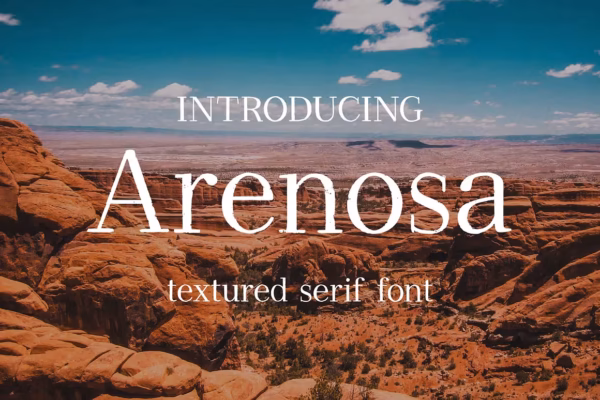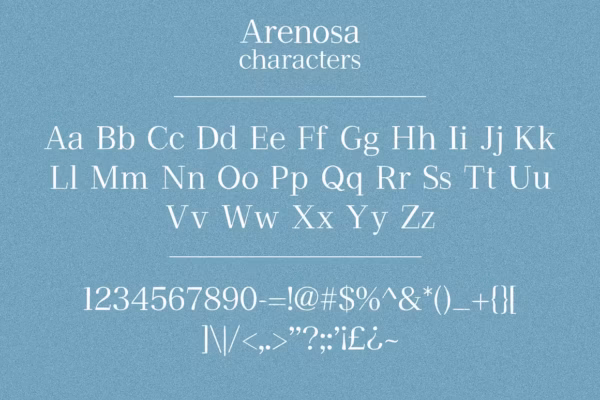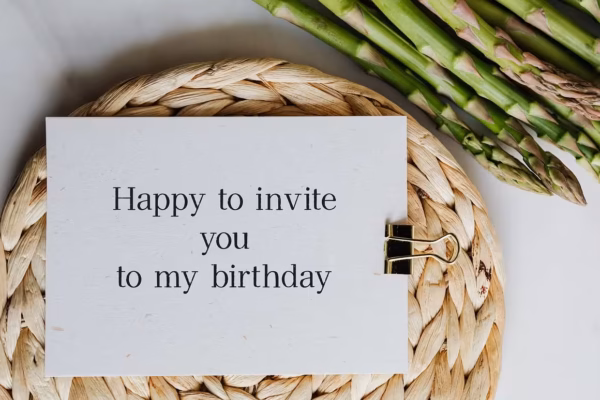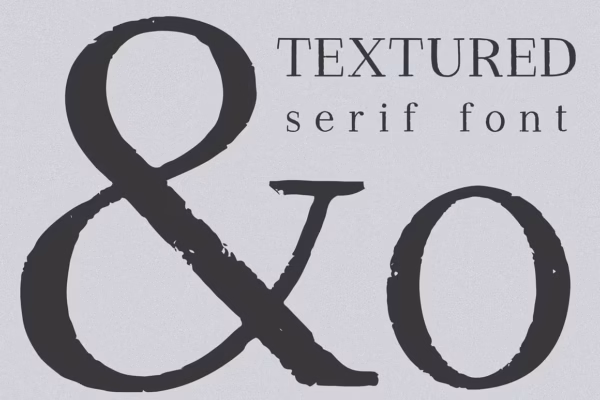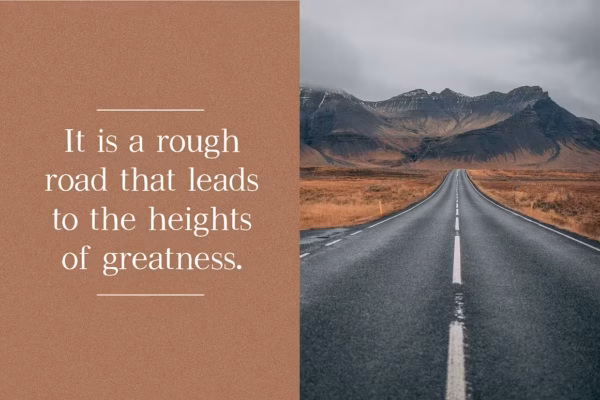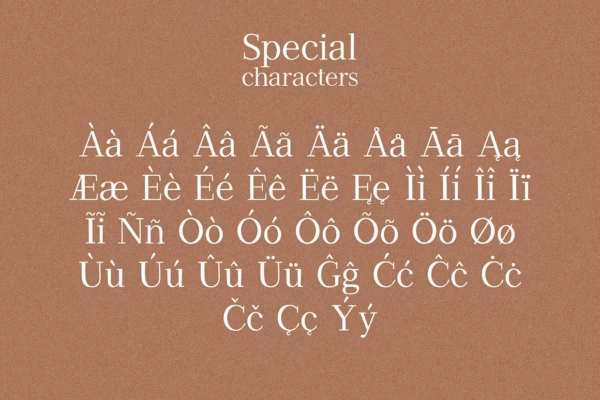
فونت سریف تکسچردار Arenosa
این یک فونت دست نویس ساده با تکسچر است. این فونت برای استفاده در عنوانها، نقلقولها و عبارات بسیار مناسب است. همچنین در لوگو، لیبل، سرتیتر، پوستر و چاپ روی تیشرت نیز جلوه زیبایی خواهد داشت. فونت Arenosa شامل حروف بزرگ و کوچک انگلیسی، اعداد، علائم نگارشی و همچنین کاراکترهای چندزبانه است.